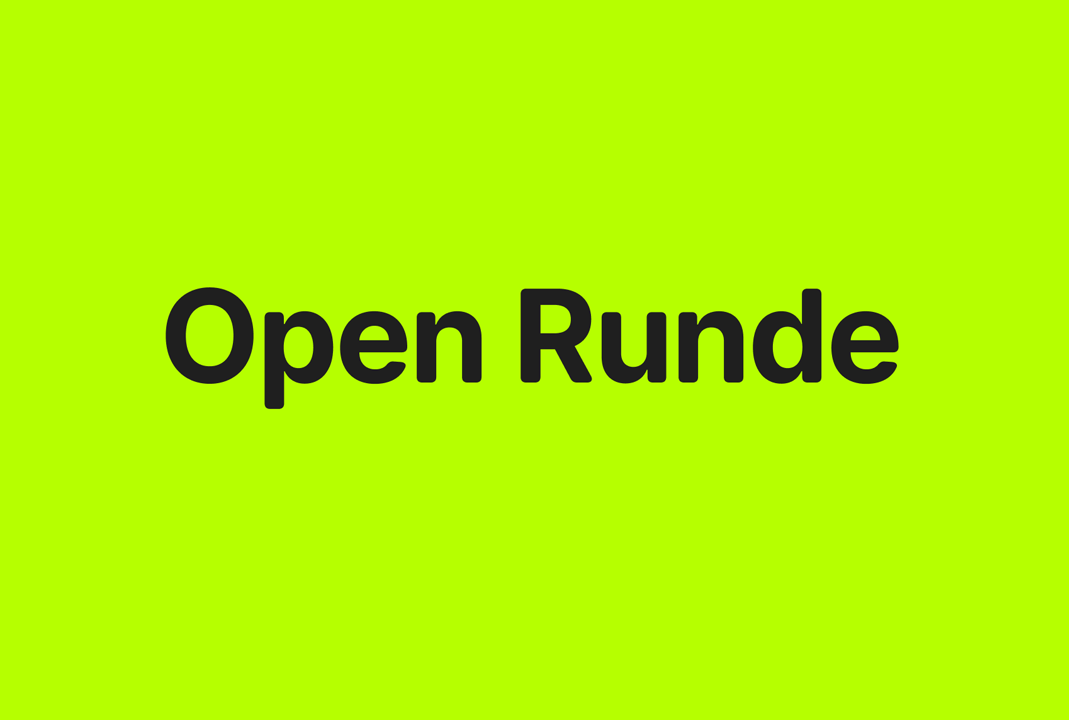
开源字体 | Open Runde 免费商用英文体下载
Open Runde 是开源英文字体 Inter(作者:Rasmus Andersson)的圆形变体。
Open Runde 是由 Glyphs Mini 工具自动生成,因此某些字形可能看起来并不完美。该字体最初被称为 Inter Soft,但为了不与原来的 Inter 字体和商标冲突而重命名。